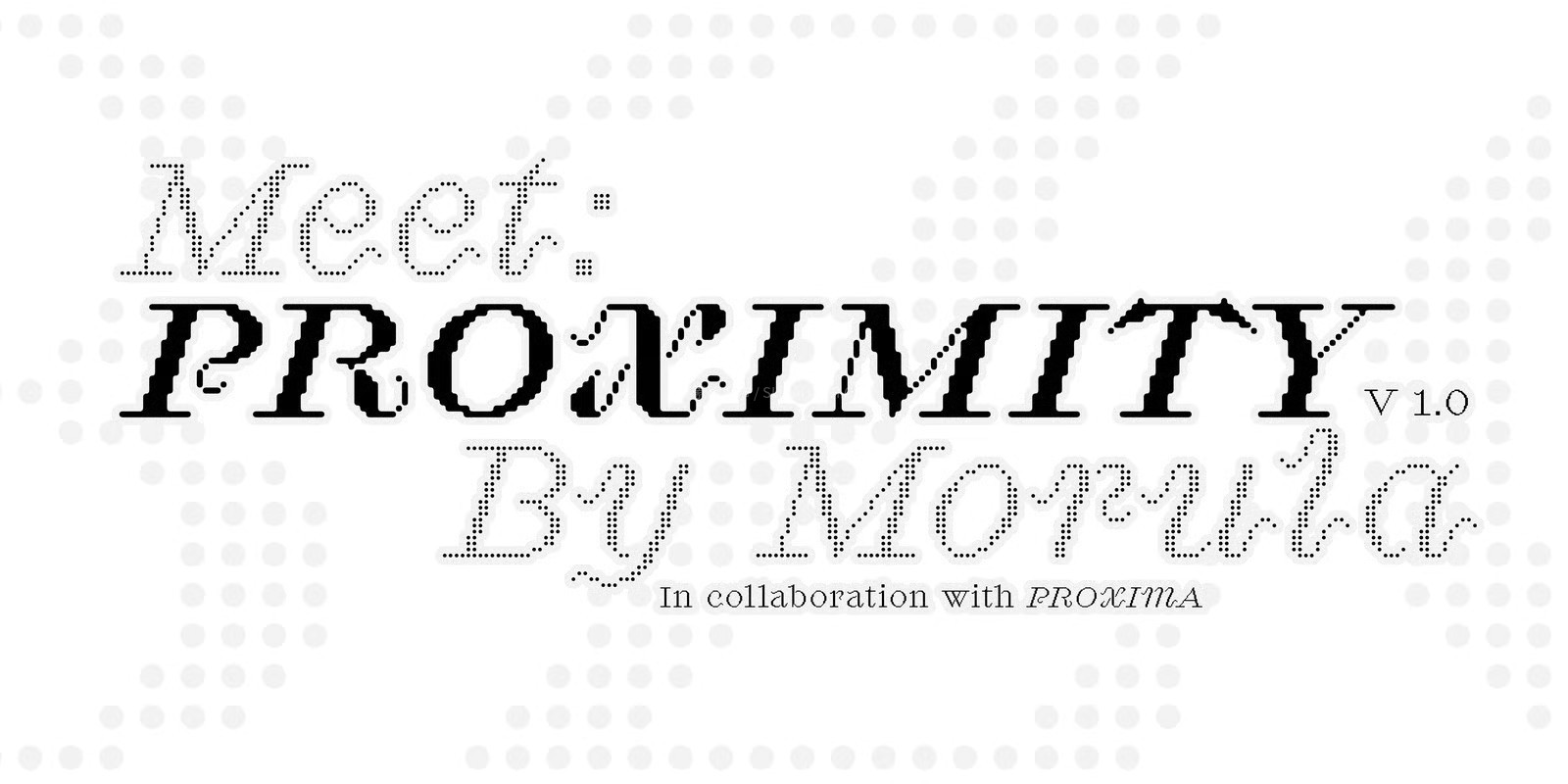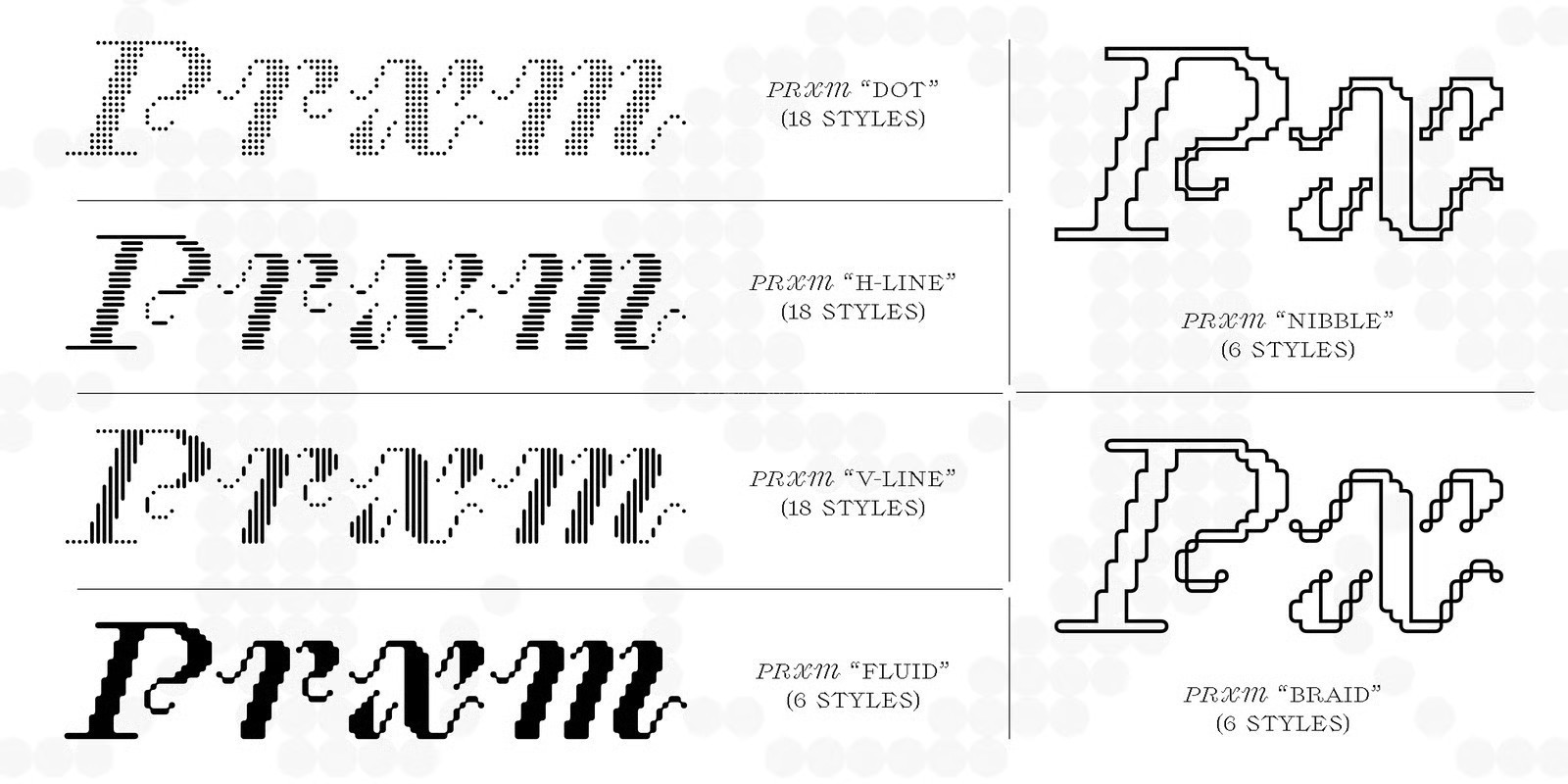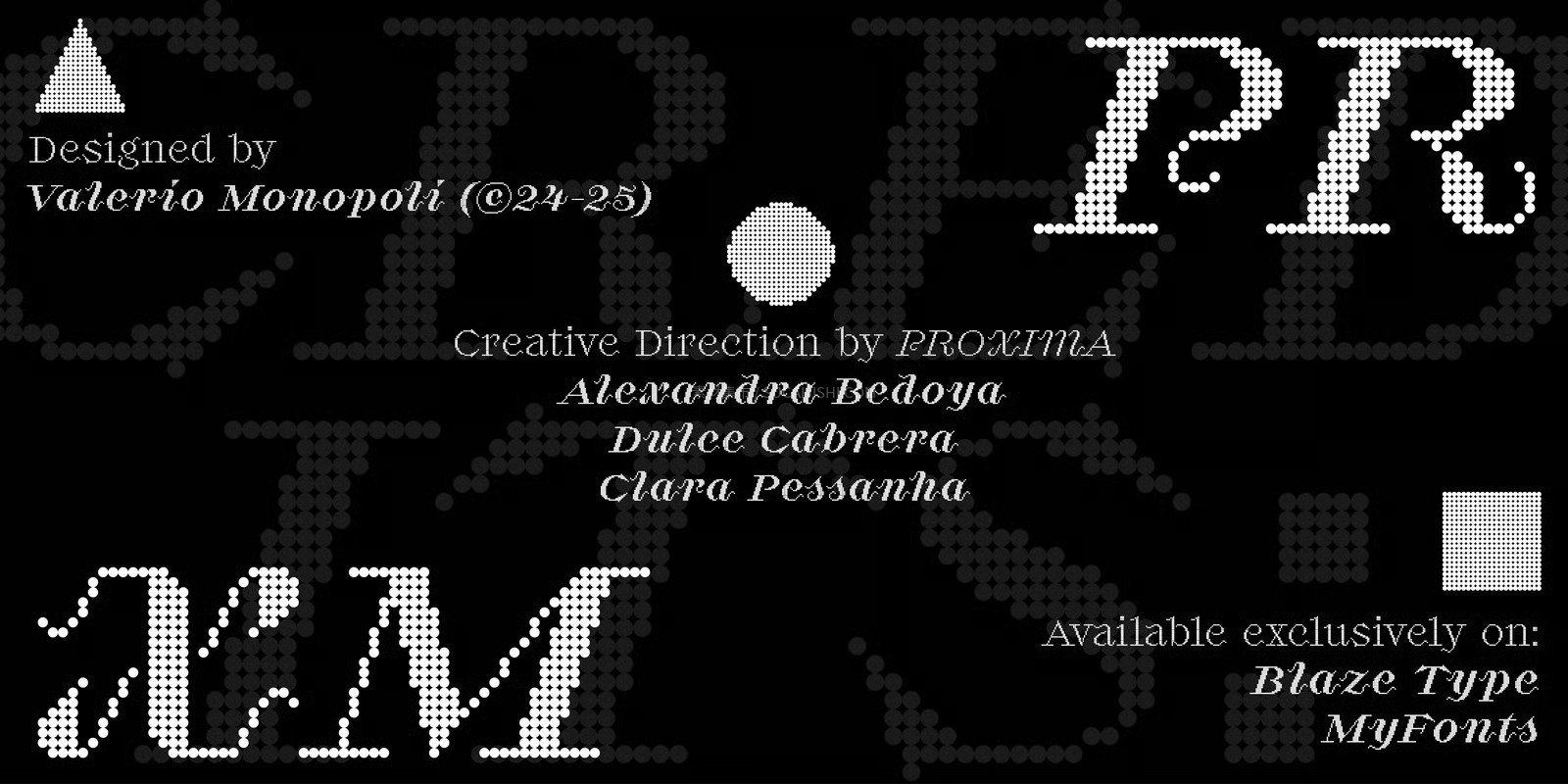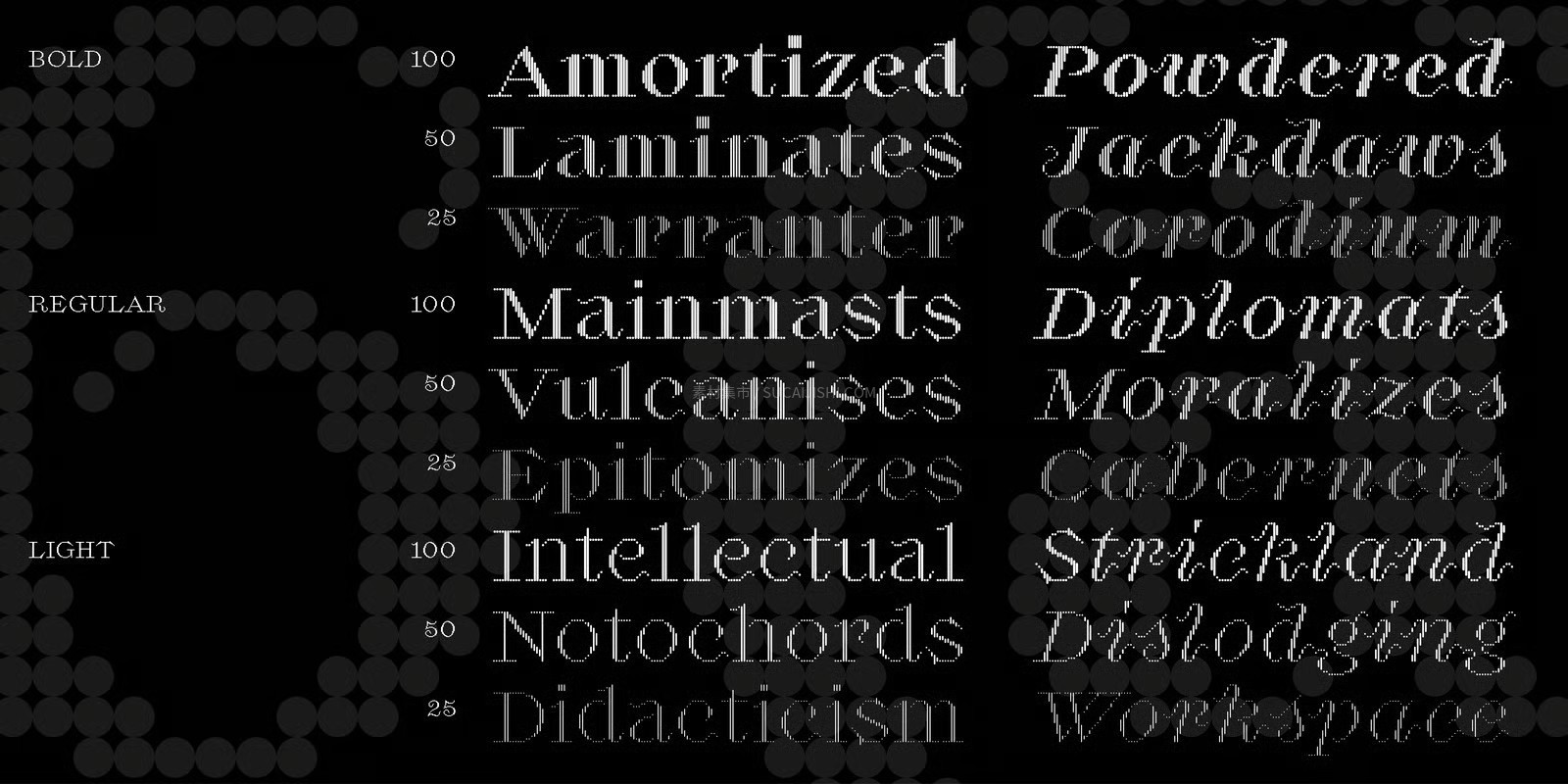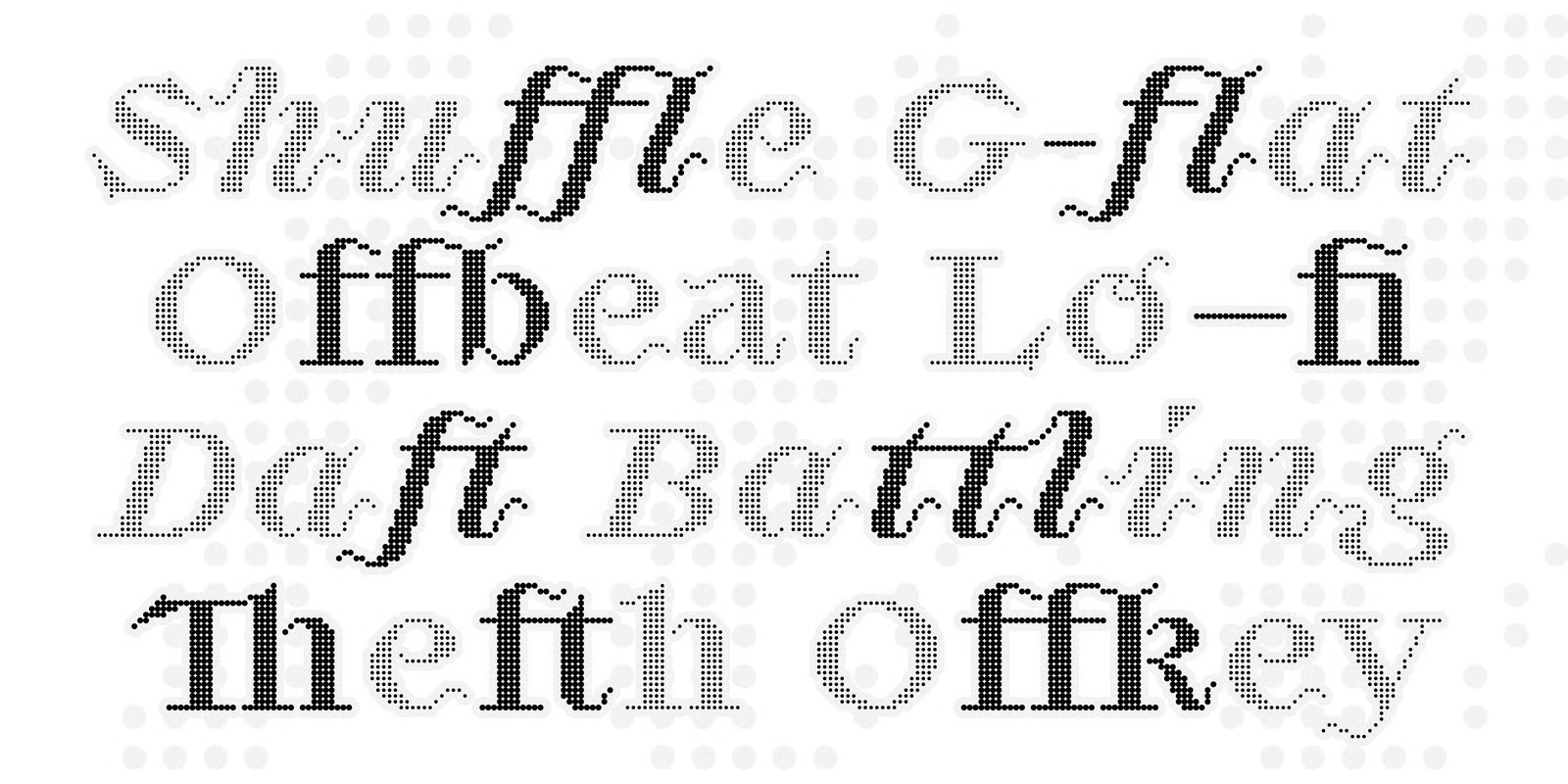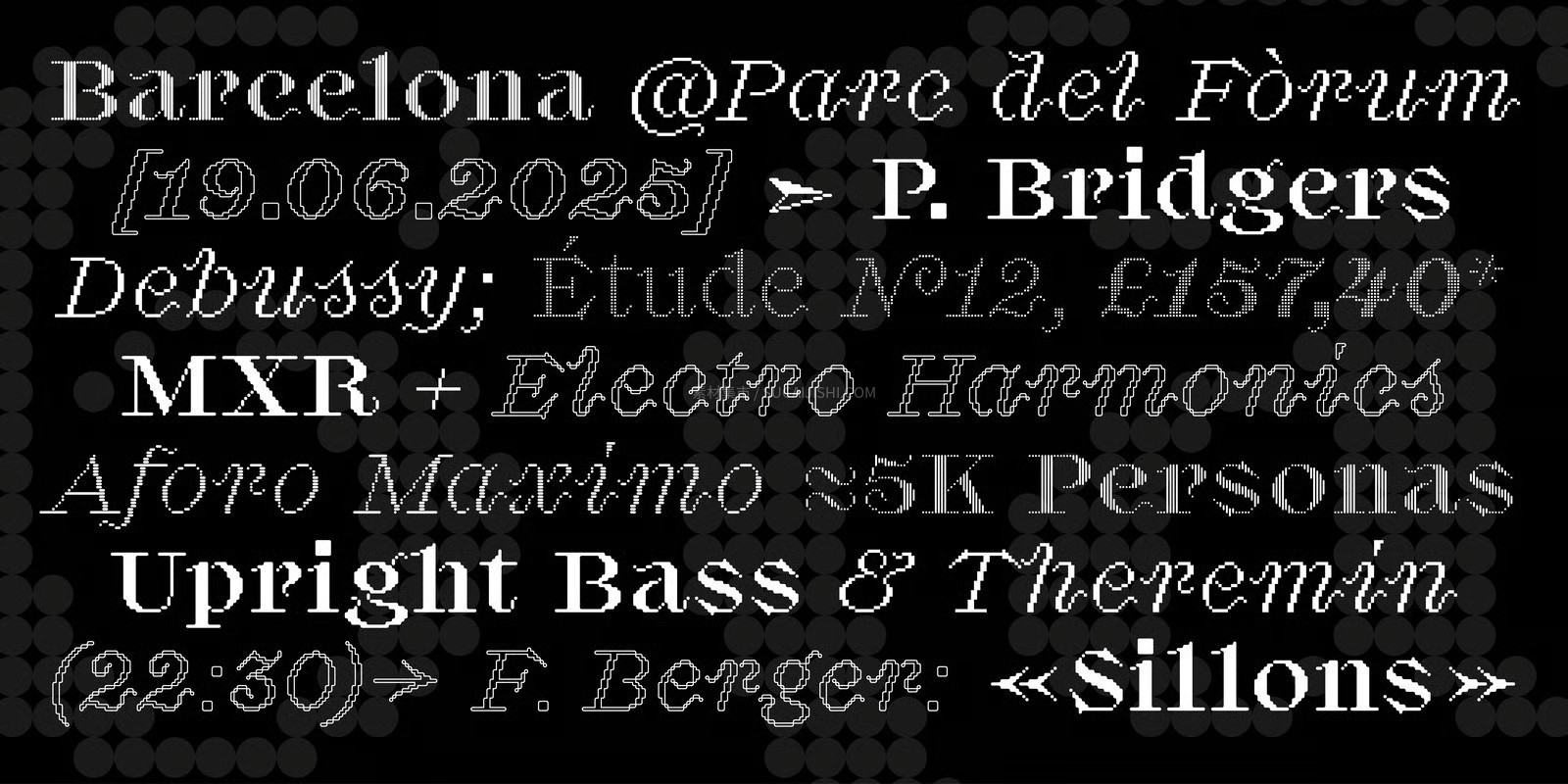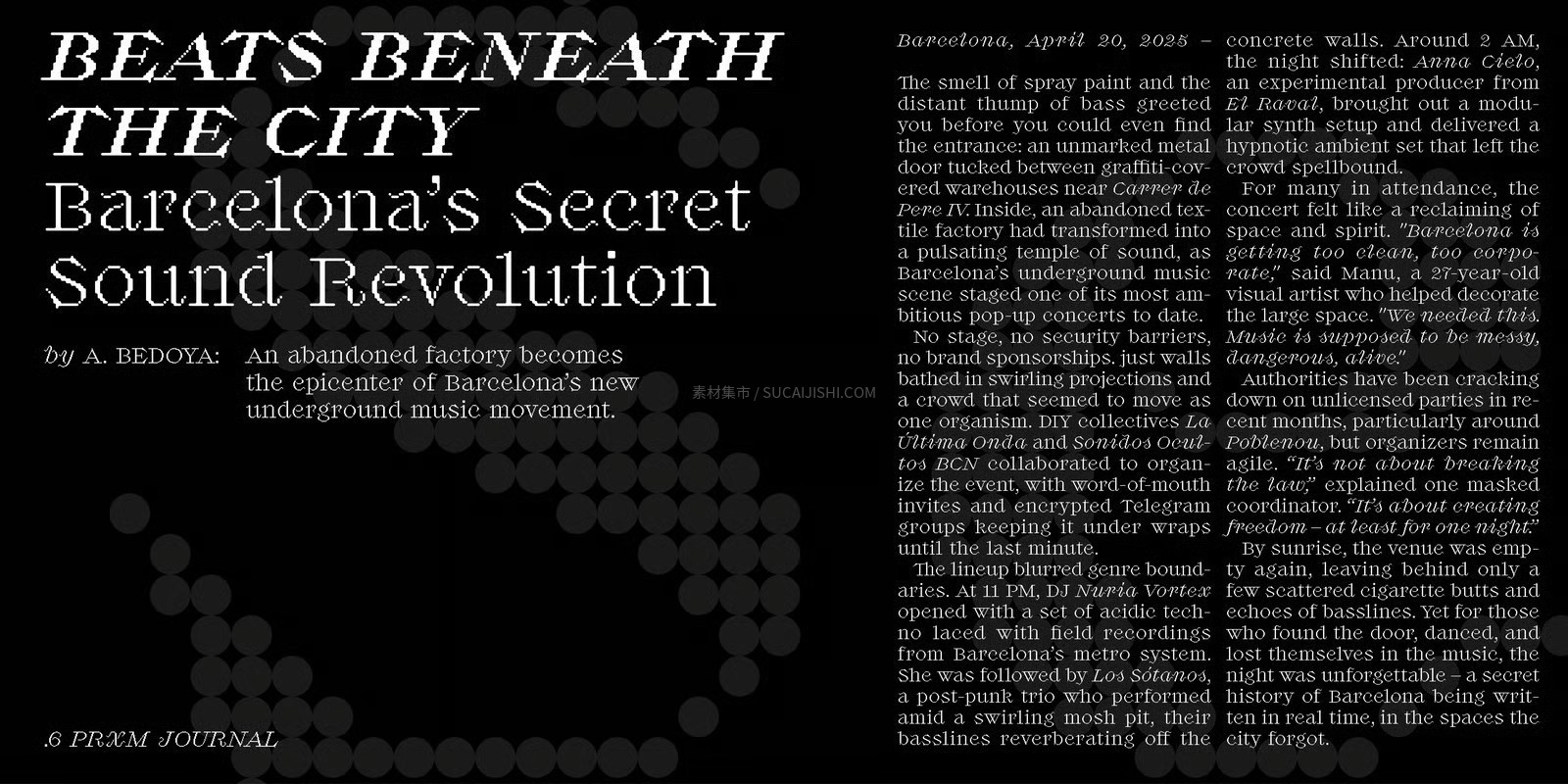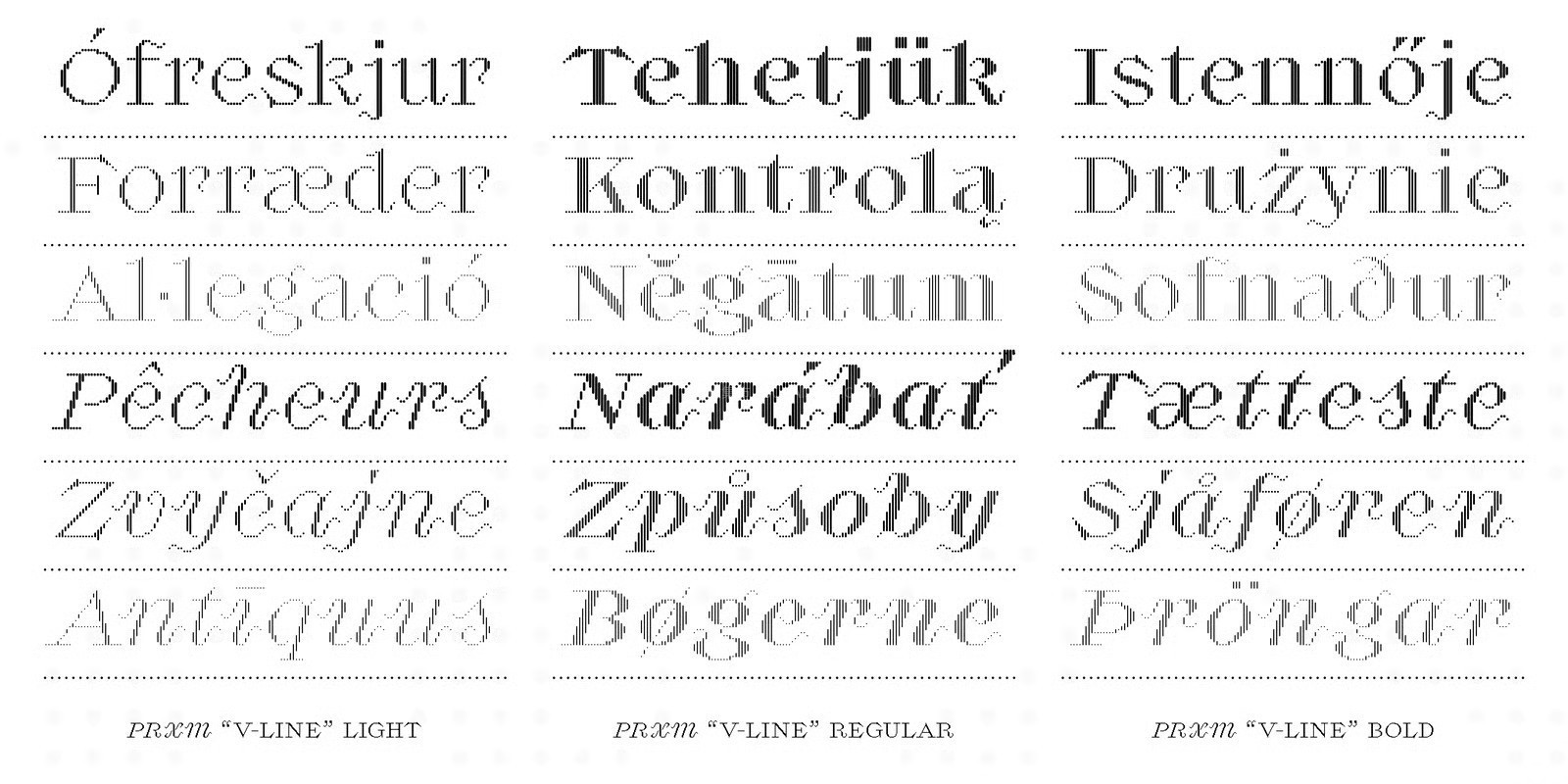
Proximity 古典像素字体家族
一款设计感直接拉满的超级字体家族——Proximity!从最初的像素风,它现在已经进化成了一个包含7个子系列、足足90种风格的庞大字库!里面不仅有经典的像素形态,还衍生出了线条构成、流畅平滑形态以及极具张力的轮廓样式。最绝的是,它打破了传统“电脑8位像素风”的刻板印象,骨子里其实是一款极其精致的衬线体,把复古像素和古典排版的优雅结合得刚刚好!它还提供静态和可变字体(Variable Font)格式,像素大小都能自由调节,拿来死磕排版细节或者做动态图形(Motion Graphics)简直是神器,视觉设计师们千万别错过!